Шрифти в illustrator
Шрифт являє собою повний набір символів (букв, цифр та інших знаків), що мають однакову товщину, шириною і стилем. Приклад: Adobe Garamond Bold 10 пунктів.
Гарнітури (що також звані сімействами тексту або сімействами шрифтів) є наборами шрифтів, мають спільний загальний вигляд і розроблені для використання разом (наприклад, Adobe Garamond).
Стиль шрифту - це варіант конкретного шрифту в гарнітурі. Зазвичай члени сімейства шрифтів, що мають в назві слово Roman або Plain (в різних гарнітурах по-різному), являють собою базовий шрифт, який може включати в себе різні стилі: regular (звичайний), bold (жирний), semibold (напівжирний), italic (курсив) і bold italic (жирний курсив).
Для шрифтів мови CJK ім'я стилю шрифту часто визначається варіацією його ширини (яка також називається товщиною). Наприклад, для японського шрифту Kozuka-Mincho Std є шість варіантів товщини: надтонкий, звичайний, середній, напівжирний і жирний. Псевдонім стилю шрифту залежить від його виробника. Кожен стиль шрифту представляє собою автономний файл. Якщо файл стилю шрифту не встановлено, то такий стиль не вдасться вибрати в меню «Нарис».
шрифти OpenType
Для шрифтів OpenType відображаються значком.
При роботі зі шрифтом OpenType ви можете автоматично замістити варіанти накреслення, наприклад, лігатури, великі літери, дріб і пропорційні фігури старих стилів.
Постійні (зліва) і шрифт OpenType (справа)
A. Порядкові числівники B. Додаткові лігатури C. Каліграфічні накреслення
Швидко знаходите часто використовувані шрифти завдяки додаванню окремих сімейств шрифтів в обране або за допомогою списку недавно використовуваних шрифтів. Нещодавно використовувані і позначені шрифти зберігаються для всіх сеансів Illustrator.
Область пошуку шрифтів можна звузити за допомогою функції їх фільтрації за критеріями (наприклад, із зарубками, без зарубок або рукописні). Крім того, можна виконувати пошук серед шрифтів, встановлених на комп'ютері або синхронізованих з Typekit.
Інший спосіб: знайдіть шрифтів на основі візуального подібності (). Шрифти, найбільш подібні до потрібним шрифтом, з'являться в верхній частині результатів пошуку.
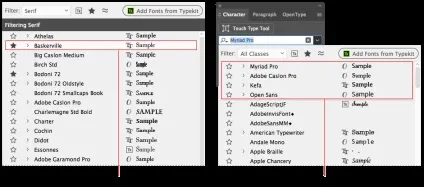
A. Додавання шрифтів в обране B. Нещодавно використані шрифти
Інструменти для пошуку шрифтів
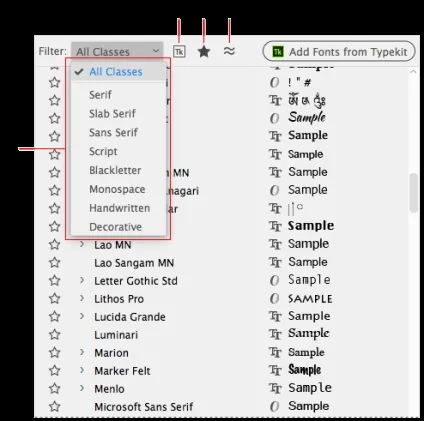
A. Фільтр B. Застосувати фільтр Typekit C. Застосувати фільтр обраного D. Застосувати фільтр за зовнішньою подібністю
Фільтрація списку шрифтів за критеріями (наприклад, із зарубками, без зарубок і рукописні).
Якщо в документі використані шрифти, не встановлені в системі, то при відкритті документа видається попередження. Illustrator вказує, які шрифти відсутні, і заміняє їх доступними придатними шрифтами.
- Щоб замінити відсутній шрифт на інший, виділіть текст з відсутнім шрифтом і застосуєте до нього будь-який інший доступний шрифт.
- Щоб виділити замінені шрифти рожевим кольором, виберіть пункт Файл> Текст і виберіть Виділити замінені шрифти (і при необхідності «Виділити підставлені гліфи»), потім натисніть кнопку «ОК».
Зміна шрифта
В Adobe Illustrator CC шрифтом за замовчуванням є Myriad Pro. Шрифт за замовчуванням заданий в меню «Шрифт», на палітрі «Символ», а також в якості стандартного стилю символів на панелі "Стилі символів». Вибирається шрифт за замовчуванням, навіть якщо відкритий документ не містить цей шрифт або перед останнім виходом з Illustrator використовувався інший шрифт. Щоб вибрати інший шрифт за замовчуванням, необхідно змінити файли шаблонів за замовчуванням в Illustrator.